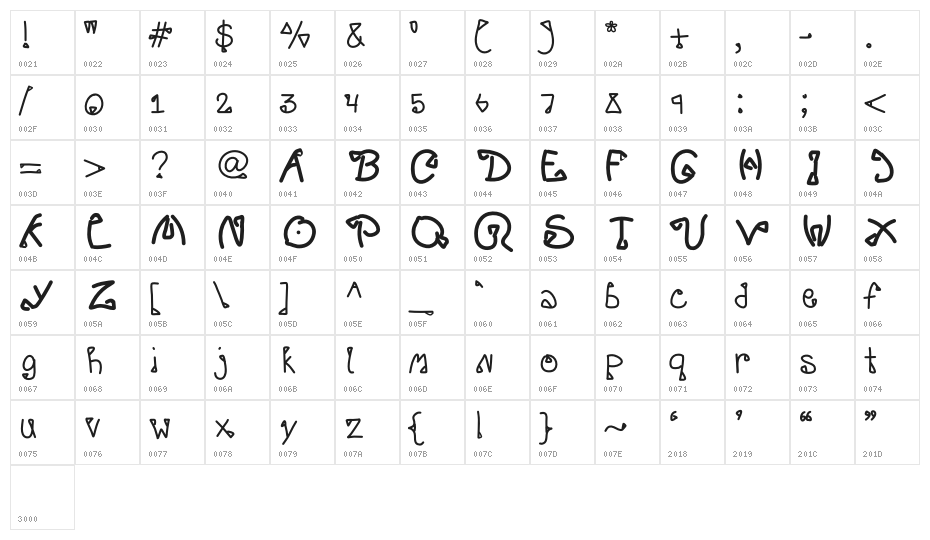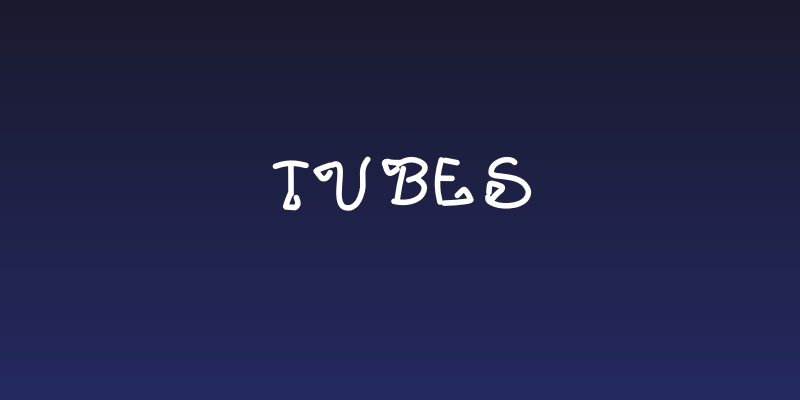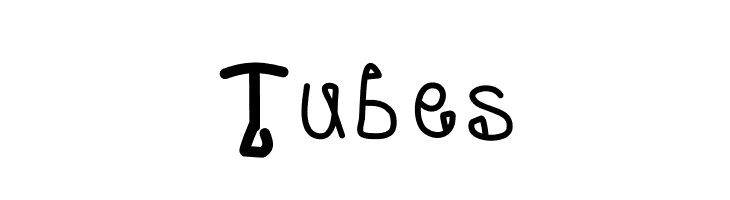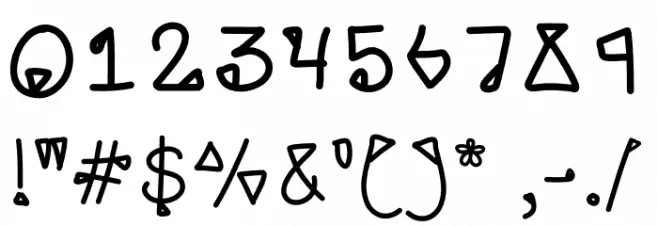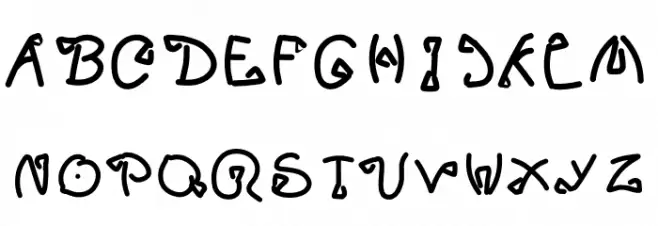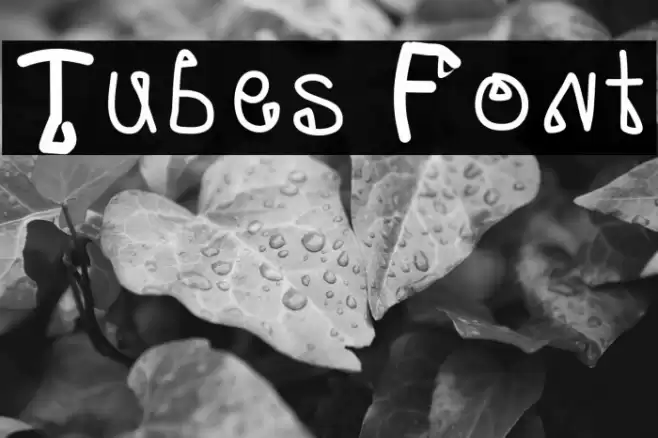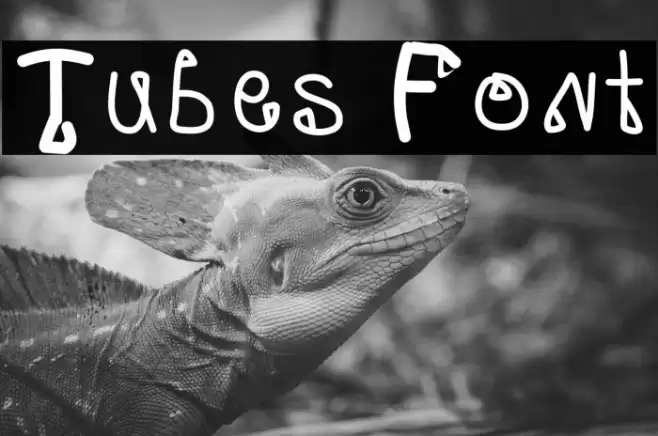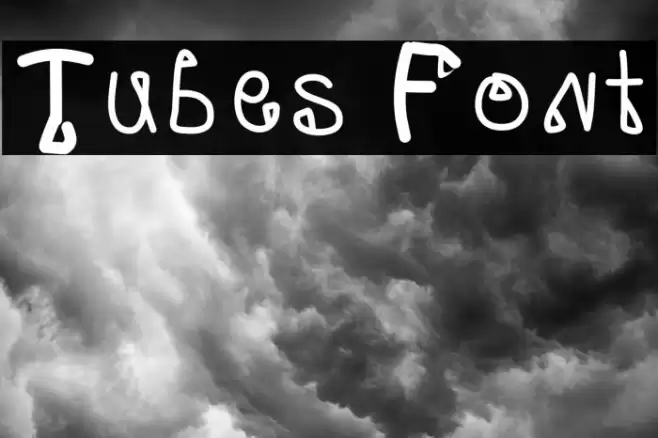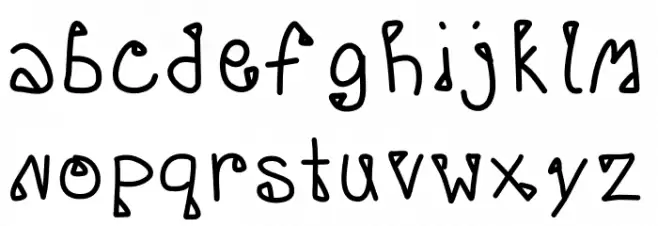
Tubes Font
| Stil general | Playful, Quirky, Hand-drawn |
| Proiecte propuse | Ideal for children's books, comic strips, playful branding, and creative posters. |